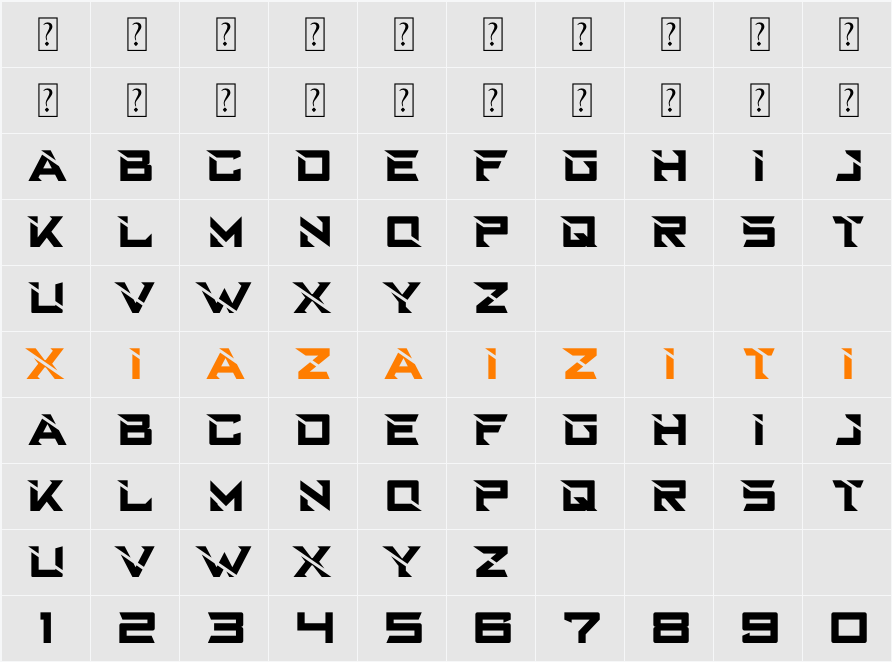
Zonex
Zonex,这款字体结构工整、笔画清晰,兼顾美观与易读性,适用于标题、正文、海报、包装、LOGO 等多种场景。字形优雅稳定,风格百搭耐看,适配日常排版与创意设计,让文字呈现更舒适、更具质感。Zonex一笔一画,皆是细节,以均衡的比例、流畅的线条打造舒适视觉体验,字形端正大气,风格简约现代。无论是商业设计、品牌宣传还是日常排版,都能轻松驾驭,让文字更有格调与力量。Zonex字体下载。